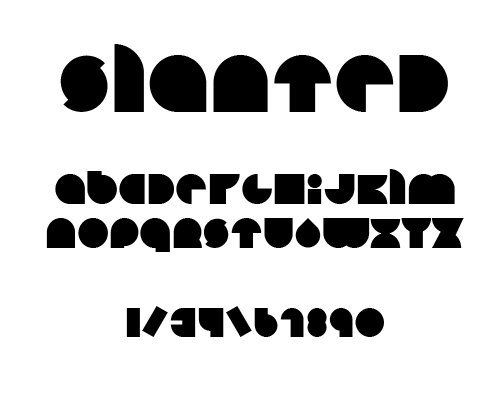
Ein frischer Font a la Neubauwelt erreichte heute unsere Redaktion. Jonathan Calugi aus Pistoia, Italien, der seine Stärken selbst in den Bereichen Illustration und Graphic Design sieht, kreierte den free-Font "happyloverstown" und bat uns um Verbreitung dessen.
Hier ein paar Impressionen!
Ist ja ganz nett, aber der Font wirkt doch etwas unfertig.
Wie soll man denn bitte das F, H und V erkennen?
In einer Headlineschrift Minuskel und Majuskel durcheinander zu werfen halte ich ja auch für etwas problematisch.
Finde es als Experiment ansehnlich, aber ob es eine Arbeit ist, die ich selbst veröffentlichen würde, wage ich zu bezweifeln. Die Illustrationen gefallen mir weitaus besser.
Ihr verbreitet hier Schriften, die nicht funktionieren und nur als
plattes Werbemittel für den amateurhaften Gestalter fungieren.